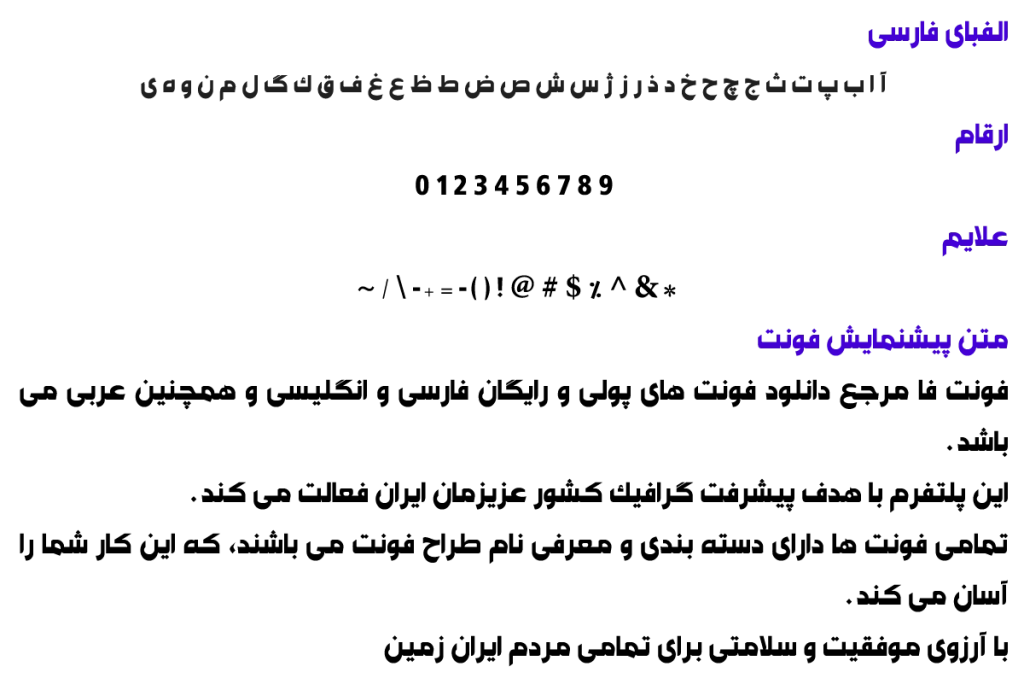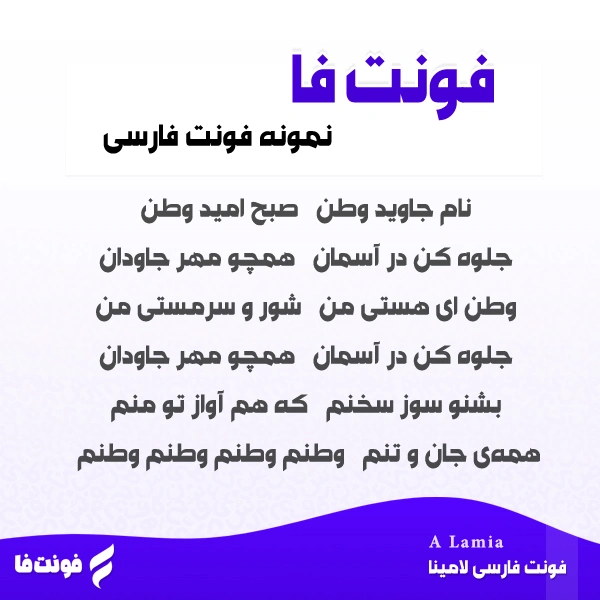
فونت فارسی لامیا – A Lamia
سال ساخت فونت: 1393
طراح فونت: ابراهیم شفیعی نوع فونت: فونت عنوان
پیشنمایش فونت لامیا
توضیحات و معرفی فونت لامیا
فونت فارسی لامیا ( A Lamia ) از مجموعه فونت های آزاد می باشد، و نیز نوع فونت عنوان می باشد.
فونت خوشگل مربوط در سال 1393 طراحی و ساخته شده است.
و نیز فونت A Lamia در یک وزن پر رنگ است.
- A Lamia Bold
نمونه ی تصویری زیر، تایپ فیس را در ترکیب با شعری میهن دوستانه نمایش میدهد.